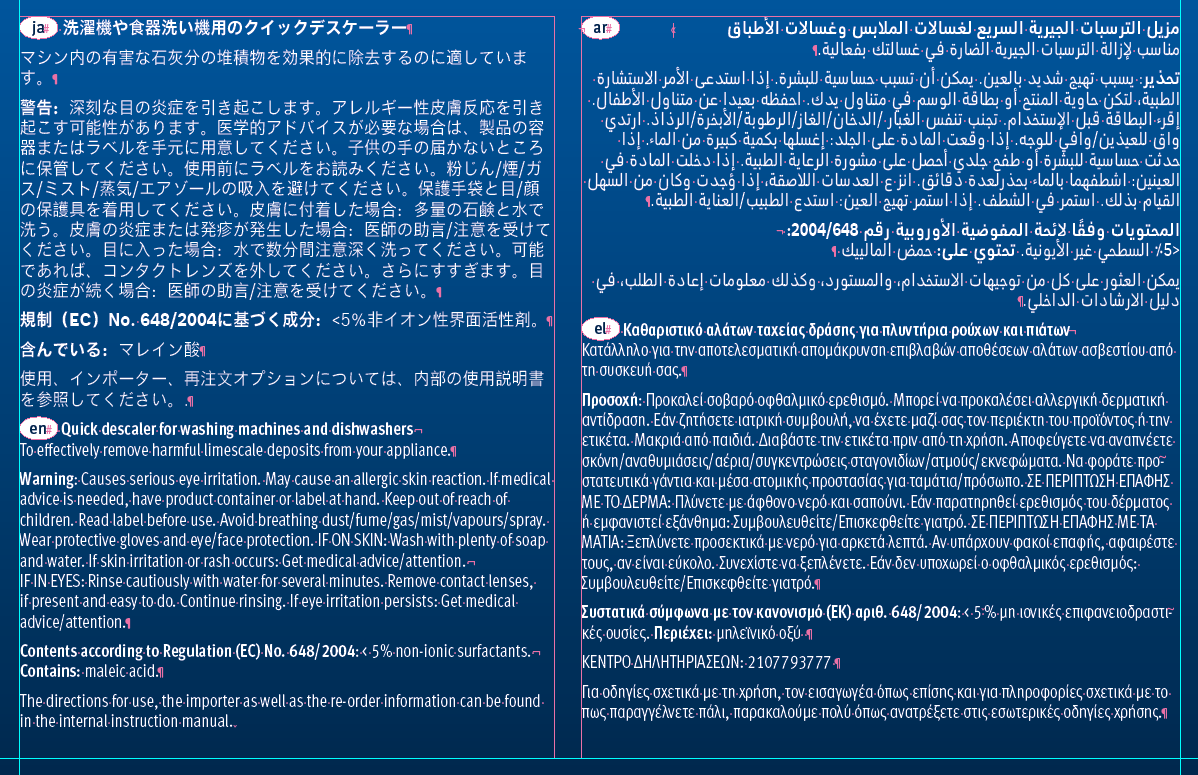
Arabische Textdarstellung. Word-InDesign. Dringend!
ich muss einen Flyer jetzt auch in arabisch setzen. Habe ein Word-Datei bekommen, allerdings werden anstatt Buchstaben nur kleine Rechtecke dargestellt. Hilfe, was muss ich denn laden, installieren, einstellen, das das funktioniert?
Also, die Worddatei zeigt mir nur Müll an!
Jetzt hab ich das Worddokument einfach in InDesign plaziert und siehe da,
das sieht ganz schön arabisch aus!
Wie das jetzt funktioniert hat weiß ich nicht! Aber es hat funktioniert :cheer:
Arabisch geht wohl in ID. Zumindest vor drei Minuten hier bei mir (CS4/WIN)
Wenn OT-Fonts mit dementsprechenden Zeichen vorhanden sind funktioniert das auch ohne dei ME-erweiterung.
Teste mal, ob Du aus der arabischen Wikipedia Texte ins ID bekommst.
Hab das jetzt mit dem PDF plazieren gemacht.
Dann stimmt es wenigstens.
wenn du mit word unter windoof dir das anzeigen lassen willst solltest du mal das Spracherweiterungspaket installieren, einfach WindowCD rein und unter Extras oder so ähnlich schauen.
Prima, InDesign ME hat ja früher ein Vermögen gekostet. Ich würde allerdings dringend empfehlen, arabische Schrift gegenlesen zu lassen. Wobei ich den Verdacht habe, dass Leute, die Arabisch sprechen und lesen, es mittlerweile gewöhnt sind, "falsch" zu lesen. Ich schau mir gerne mal internationale Verpackungen an ...
Ich habe hier noch CS4 und hatte jetzt auch das Vergnügen zumindest ein Wort arabisch zu setzen. Dass die Buchstaben in der falschen Reihenfolge waren, war für mich nicht ersichtlich aber der Dolmetscher fand das wohl höchst befremdlich was ich da gemacht habe. Wir haben uns dann mit einem PDF, das in Pfade gewandelt war, ausgeholfen. Multikulti mit allen Tücken ist jetzt auch hier am letzten Ende angekommen
Magnus, meinst Du die Lösung mit dem Textrahmen? Damit bekommt man zwar arabische Schriftzeichen, die Schreibrichtung geht aber in InDesign wirklich nur mit ME. Sprache ändern bringt nichts. Man kann das daran erkennen, dass die Buchstaben nicht verbunden sind: Arabisch, gleich welcher Schrifttyp, ist eine Kurrentschrift und wird immer verbunden. Ausnahmen sind nur bestimmte Buchstaben (rim, zin, waw, quaf, alif) und Kreuzworträtsel.
Ich hatte auch das Problem mit einzelnen arabischen Wörtern innerhalb eines Absatzes. Bei mir (CC2017) war die Lösung denkbar einfach: Globaler Adobe-Absatzsetzer auswählen, dann laufen die arabischen Wörter automatisch von rechts nach links, der Rest weiterhin normal (von links nach rechts). Adobe scheint also nachgebessert zu haben :)
weil ich's grad gebraucht habe und jetzt doch eine lösung gefunden habe (die mit den neueren ID versionen funktioniert) und damit ich den trick in 2 jahren wiederfinde, speichere ich das hier mal ab:
Habe grade ein 80-seitiges Buchprojekt auf arabisch hinter mir ...
kann bestätigen dass das mit der CC-Englisch-Arabisch-Version inzwischen tadellos klappt – wenn man erst mal die Spezifika verstanden hat (Schriftsystem, Leserichtungen, Layourichtung, Blätterrichtung, ...), und im Wissen dass man natürlich als kulturfremder Gestalter besser weniger als mehr macht ...
Wir hatten Googles Noto-Sans-Arabic im Einsatz, die 8 Gewichte und 4 Weiten mitbringt und die Opentype-Features vernünftig und modern implementiert hat – was sehr hilfreich ist. Gemischt (über composite-Fonts in Indesign) haben wir das  mit der CI-Schrift DIN Pro (Ziffern, Satzzeichen, ...).
Die Übersetzungen kamen vom Übersetzer in einem Word-docx-Dokument und zur Kontrolle nochmal als PDF um zu sehen ob das Schriftbild bei uns irgendwie zerfetzt wird – war zum Glück nicht der Fall. Ein manuelles Kopieren der Texte ins Indesign-Dokument (arabisches Dokument, Leserichtung rechts nach links, Ausrichtung rechts, Sprache Arabisch, keinesfalls "optisches" Kerning!, ...) hat dann ein nachvollziehbares Bild abgegeben, d.h. auch das hat geklappt. Stellenweise haben wir mit Google-Translate noch Plausibilitäten geprüft um mal was sinnvoll umbrechen zu können (was aber gar nicht so kompliziert ist).
Das einzige mit Hirnknoten-Potential waren einzelne westliche Worte und die Zahlen ... die Navigation mit Cursor-Tasten, aber auch mittels Maus ist da alles andere als intuitiv (egal ob im Modus "logisch" oder "optisch").
Nebeneffekt: man erkennt an einigen Stellen plötzlich, warum die deutsche Indesign-Version so "seltsam-unsinnig organisierte" Werkzeugpaletten hat – da tauchen plötzlich neue Optionen auf ...
Aber alle drei zusammen in einem Interface ... ?  Ich kann natürlich japanischen Text ins Dokument kopieren und mit den "westlichen" Mitteln formatieren und soweit ich sehe mit dem "adobe world-ready-composer" statt dem normalen Absatzsetzer auch einigermaßen gut setzen (lassen), aber wenn irgendwas spezielles gefordert wird fehlen die Interface-Elemente mit denen ich das beeinflussen könnte.
Ah, jetzt – mein ID ist nur englisch-arabisch. Japanischen Text kann ich – wie du beschrieben hast – reinkopieren und formatieren, mehr will und muss ich gar nicht.